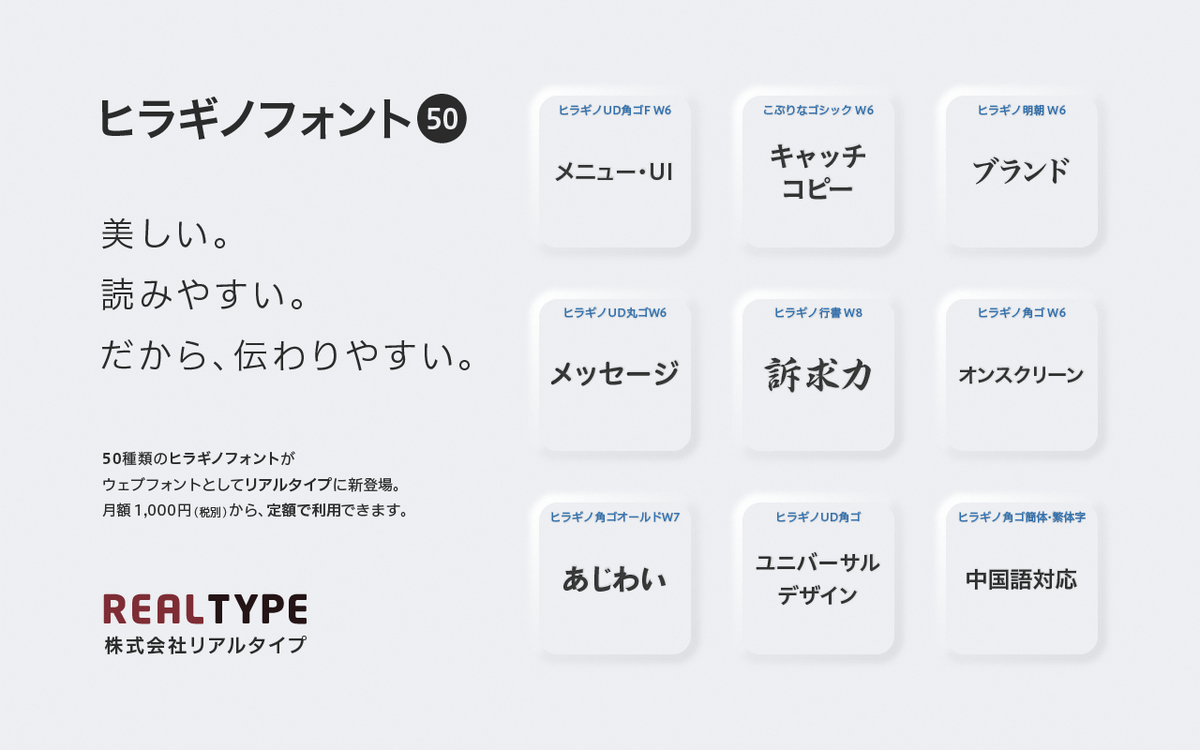
Webフォントサービス「REALTYPE」にヒラギノフォント追加
リアルタイプは、SCREENグラフィックソリューションズの「ヒラギノフォント」がウェブフォントサービス「REALTYPE(リアルタイプ)」で7月下旬より提供開始されることを発表した。
REALTYPEに搭載されるヒラギノフォントは、発売以降さまざまなシーンで利用されるフォント。新たに追加される50フォントはゴシック体、明朝体、丸ゴシック体、ユニバーサルデザイン書体、行書体、簡体字フォント、繁体字フォントなど幅広いバリエーションとなっている。
REALTYPEにヒラギノフォントが搭載されることで、OSやデバイスを問わず、定額でヒラギノフォントがウェブフォントとして利用可能になる。
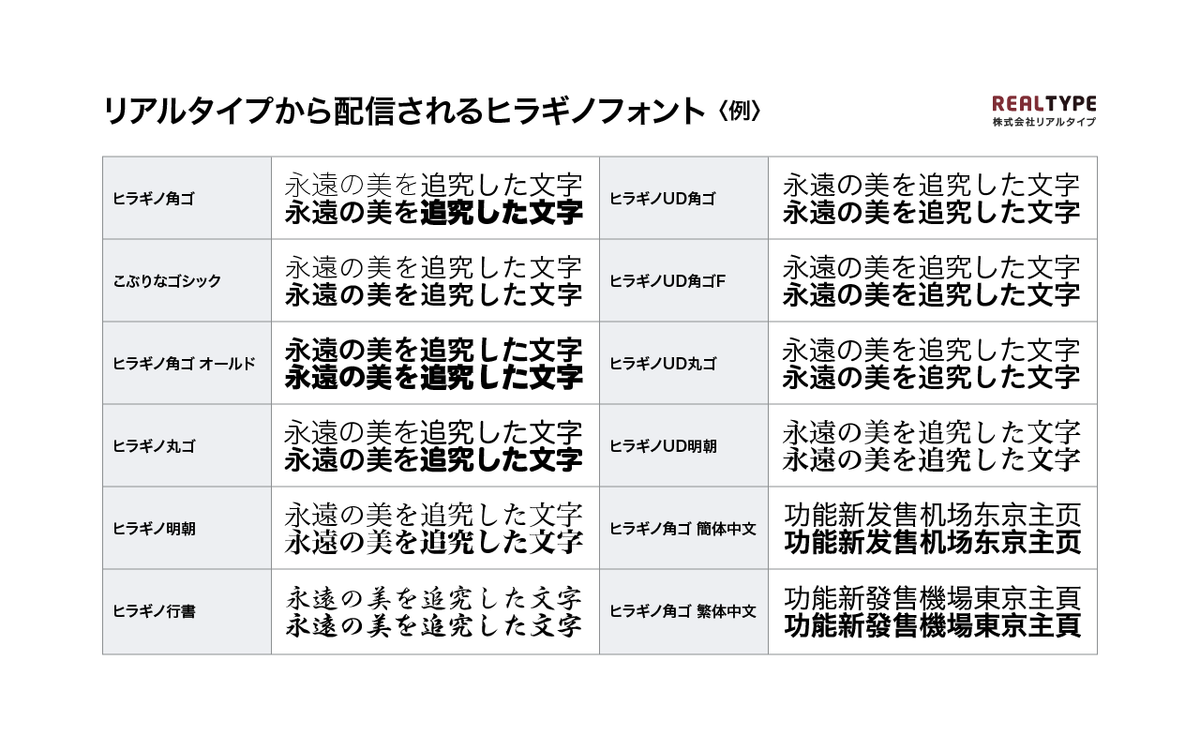
ヒラギノフォントの特徴
「ヒラギノ角ゴ」は、シーンを選ばないスタンダードなフォントとして、コーポレートフォントから映像メディアの情報表示まで、幅広いシーンで活躍する。世界中で利用されるスマートフォンやOSの表示に標準で利用されているフォントでもある。
「ヒラギノ明朝」は、モダンな表情を持つ明朝体。コーポレートフォントのほか、広告、企業や製品のブランドイメージを支えるフォント。
「ヒラギノ丸ゴ」は、ヒラギノファミリーのシャープでモダンな印象を持つ丸ゴシック体。ポップすぎない印象は、カタログやマニュアルなどで活用されている。ヒラギノ角ゴ、ヒラギノ明朝と同様に、全世界でシェアのあるOSに日本語表示フォントとして標準で搭載されている。
「ヒラギノUD角ゴ」「ヒラギノUD明朝」「ヒラギノUD丸ゴ」は、読みやすさと誤読の防止に配慮したユニバーサルデザイン書体。ヒラギノファミリーの特徴を保ちつつユニバーサルデザインに配慮したフォント。
「ヒラギノUD角ゴF」は、明るくすっきり見える「フラット」「ファイン」がコンセプトのユニバーサルデザインフォント。
「ヒラギノ角ゴ オールド」は、金属活字に由来する仮名により、力強さと懐かしさを感じるフォント。
「こぶりなゴシック」は、柔らかく丸味をもったゴシック体でエディトリアルやパッケージデザイン、広告のキャッチコピーなど、デザイナーの間で人気のあるフォント。
「ヒラギノ行書」は、華やかさと力強さが特徴の行書体。優雅さと読みやすさを両立し、縦でも横でも美しく組める特徴がある。
「ヒラギノ角ゴ 簡体中文」「ヒラギノ角ゴ 繁体中文」は、ヒラギノ角ゴのコンセプトを継承し、中文フォントの中でも現代的なデザインのゴシック体です。簡体中文はGB認証も取得していることから、グローバル向けのコーポレートサイトやブランドサイトなどで活躍するフォントとある。